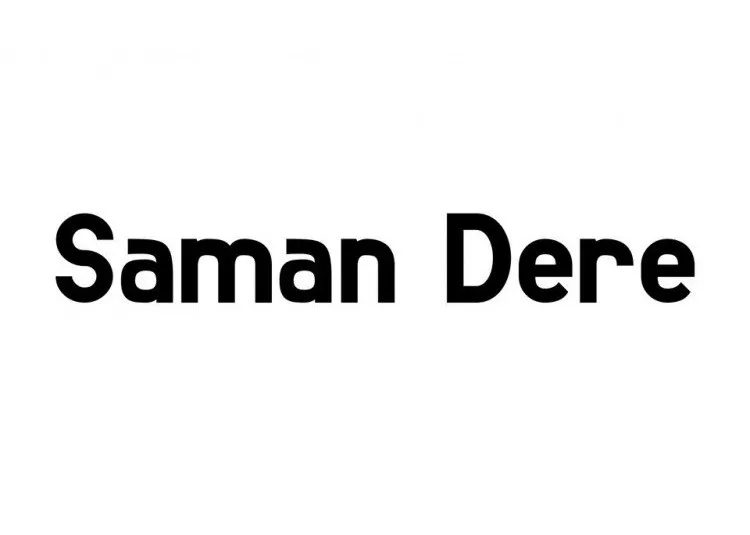
A ‘Saman Dere’ é uma nova adição à família das fóntes sans serif que oferece uma experiência visual única para seus trabalhos digitais. Inspirada nos estilos dos headlines de jornais antigos, essa elegante fónte é projetada para ser minimalista e possui um design de qualidade. Suas formas são perfeitamente adaptadas às telas digitais modernas, garantindo legibilidade ótima em qualquer dispositivo. Com mais de 350 caracteres disponíveis e suporte a quarenta e dois idiomas diferentes, ‘Saman Dere’ é uma escolha versátil para designers de todo o mundo que buscam um estilo clean e sofisticado para suas criações digitais. Esta fonte representa perfeitamente a evolução da sans serif, proporcionando aos designers uma ferramenta poderosa para expressar sua visão visual em formatos digitais de maneira clara e moderna.